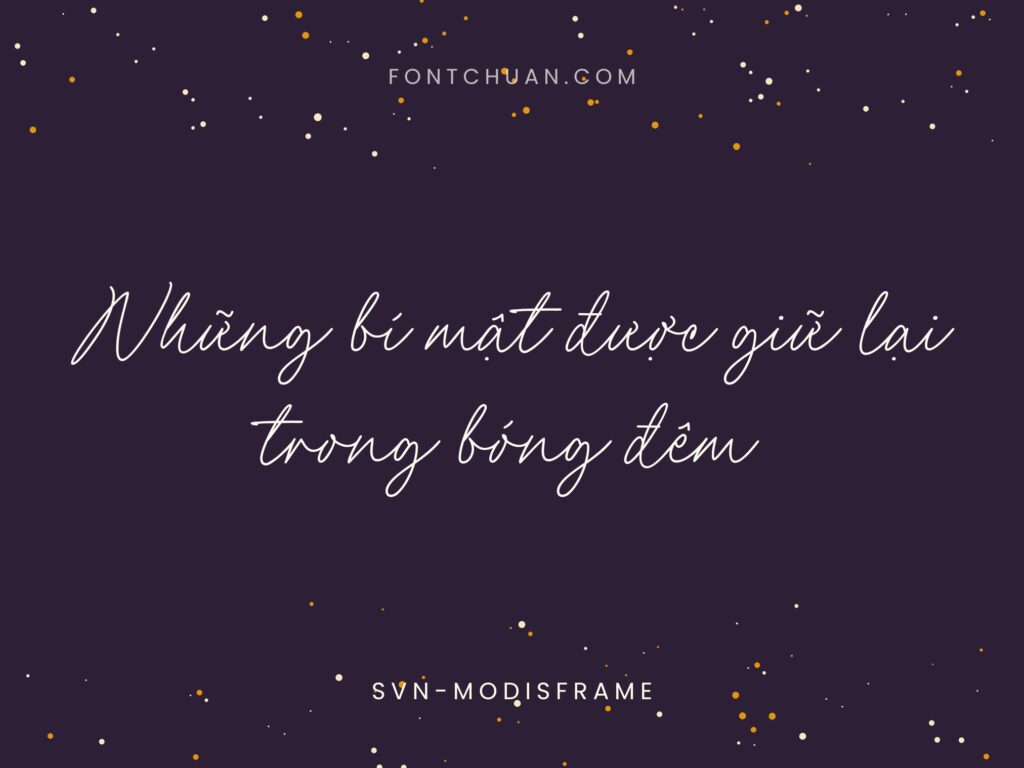
Font SVN Modisframe Việt Hóa
Tác giả Font: Cititype
Font SVN Modisframe là phiên bản Việt hóa của kiểu chữ Modisframe, được thực hiện bởi STYLEno.1 Fonts. Modisframe là một font chữ ký hiện đại với nét đơn mảnh, mang phong cách viết tay thanh lịch và tinh tế. Font này bao gồm 100 ligature hỗ trợ đa ngôn ngữ, tạo nên sự tự nhiên và liền mạch trong từng ký tự. Modisframe phù hợp cho nhiều mục đích sử dụng khác nhau như thiết kế chữ ký số, thiệp mời, nhãn hiệu sản phẩm và các ấn phẩm quảng cáo.
SVN Modisframe lý tưởng cho các dự án thiết kế yêu cầu sự thanh lịch và cá nhân hóa, như thiết kế chữ ký số, thiệp mời, nhãn hiệu sản phẩm và các ấn phẩm quảng cáo. Các ngành nghề như thiệp cưới, giáo dục và bất động sản có thể tận dụng font này để tạo điểm nhấn trong thiết kế. Ngoài ra, font cũng thích hợp cho các sự kiện như Valentine, Sinh nhật, Tết và các lễ hội khác.